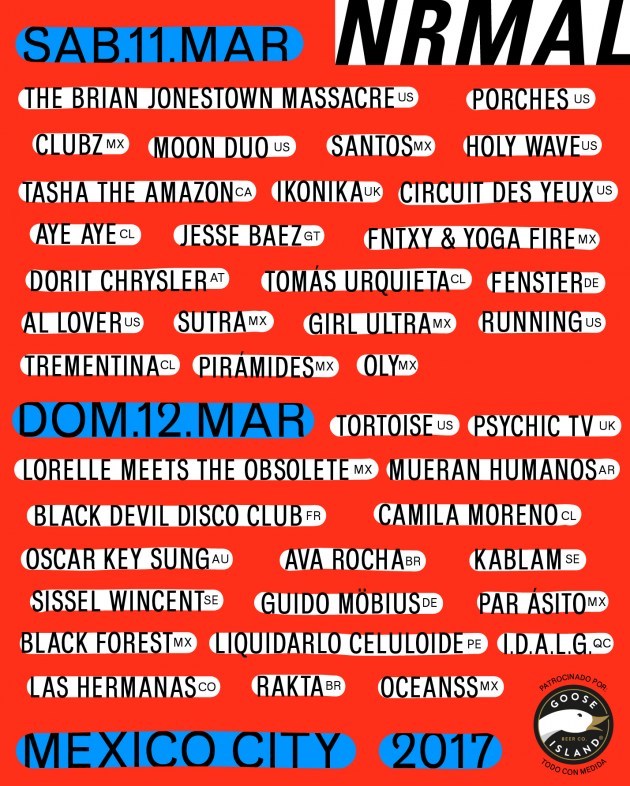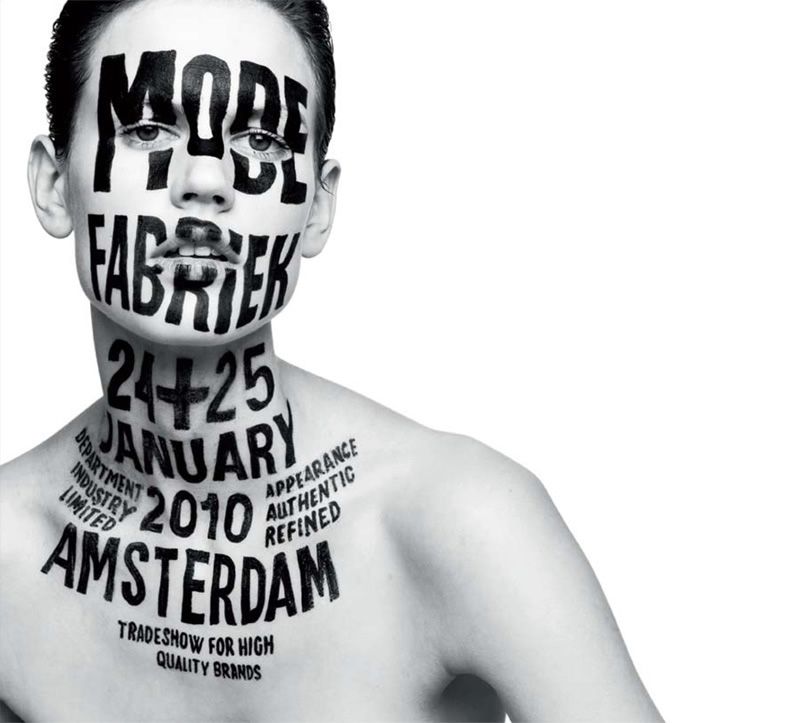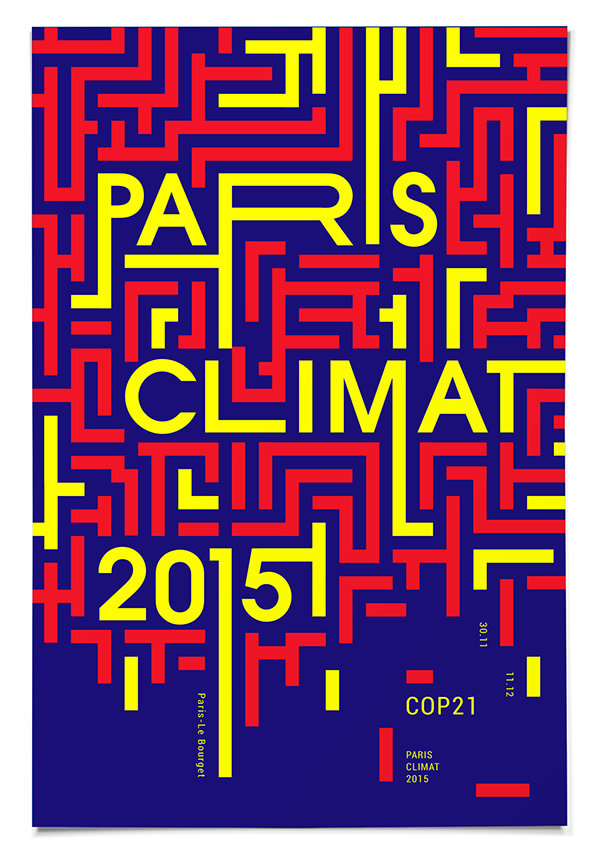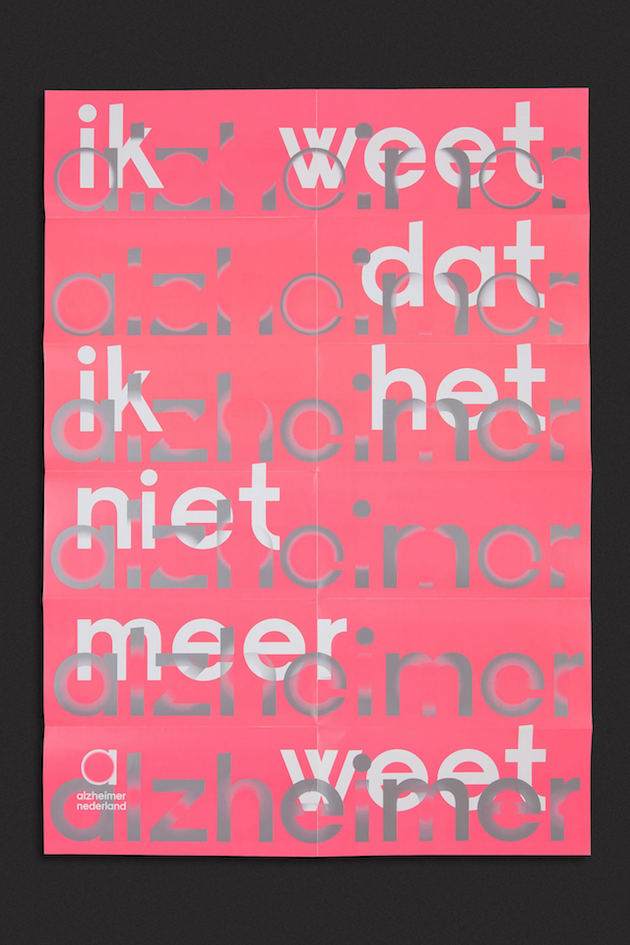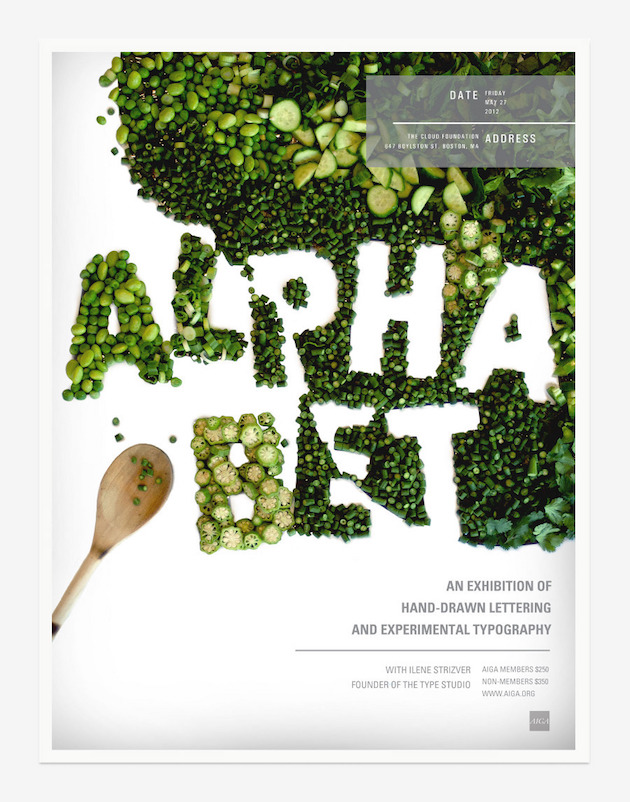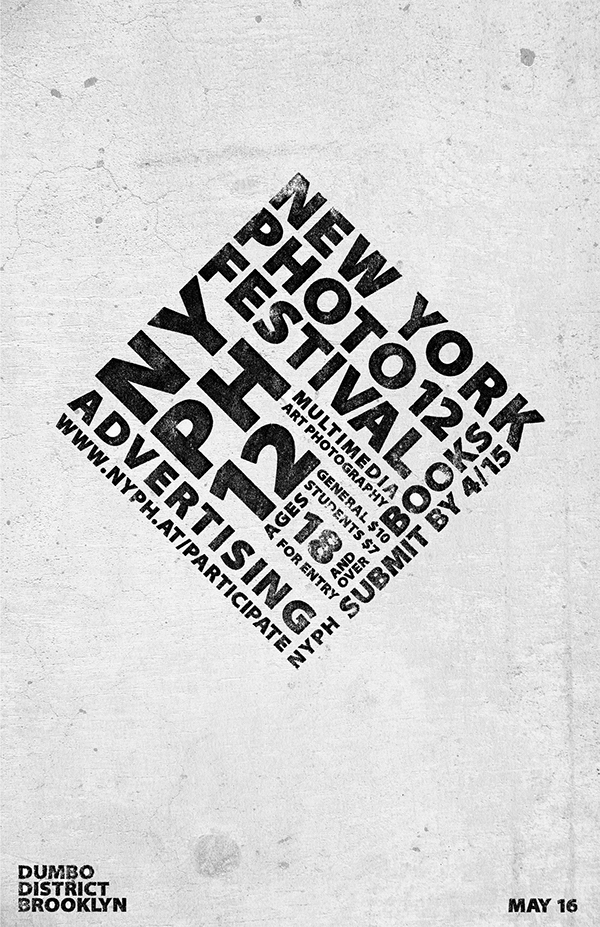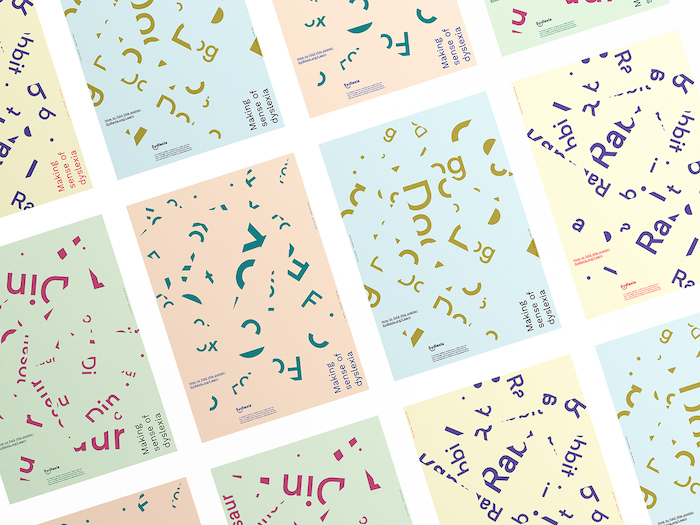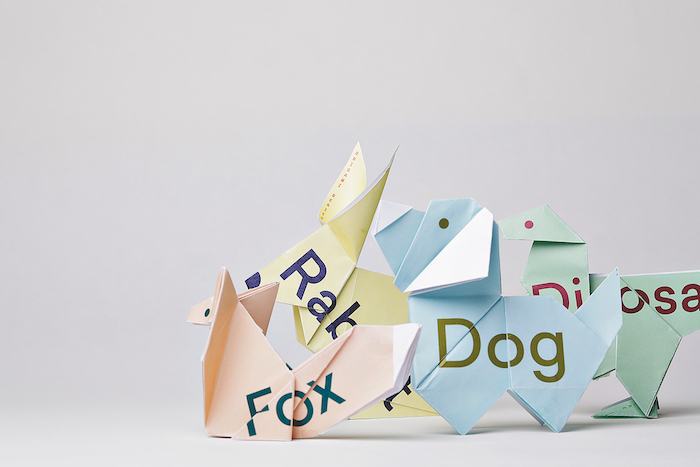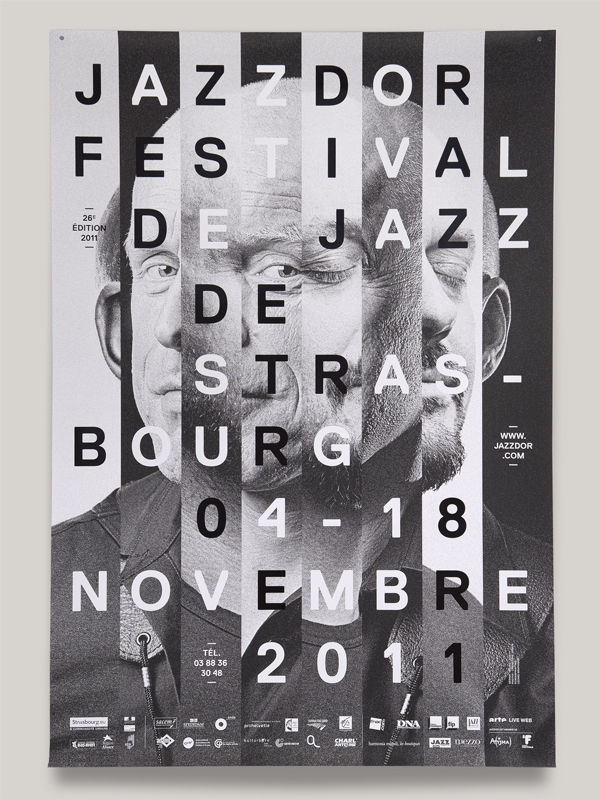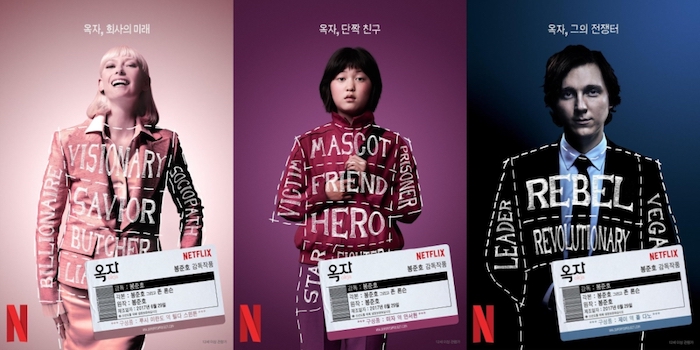
10 affiches publicitaires qui utilisent la typographie avec brio
Une affiche publicitaire, ce n’est pas que des photos ou des illustrations, c’est aussi du texte !
D’où l’importance capitale de la typographie pour créer un poster qui attire l’œil et qui reste gravé dans la mémoire.
Voici justement 10 exemples d’affiches qui utilisent brillamment le texte et les polices d’écriture.
Nrmal est un festival de musique qui a lieu chaque année à Mexico.
Les affiches promotionnelles de l’événement utilisent toujours le texte de manière très prononcée (et efficace), afin de présenter les différents artistes qui y participent, comme en témoigne l’affiche de l’édition 2017.
Créée par Studio Dumbar pour une organisation néerlandaise de lutte contre la maladie d’Alzheimer, cette affiche utilise brillamment la typographie pour communiquer sur ce sujet difficile.
En effet, les caractères flous et partiellement effacés symbolisent la perte de mémoire et l’âge, tout en pouvant être perçus comme une lueur d’espoir.
Toute l’originalité de cette affiche – réalisée par Kittaya Treseangrat – vient des lettres dessinées avec des légumes (ou à l’aide de l’espace vide), lui conférant un aspect vraiment unique.
En parallèle, des polices d’écritures simples et sobres sont utilisées pour le texte d’accompagnement (en haut et en bas à droite) afin de ne pas surcharger le visuel.
Cette affiche utilise habilement le texte pour créer une forme carrée qui ne manque pas d’attirer l’œil et de susciter l’intérêt.
La typographie se veut quant à elle assez sobre, en termes de couleur et de forme ; seul un effet « abîmé » lui a été appliqué, en accord avec le fond grisâtre et fissuré.
À l’instar de l’affiche pour Alzheimer Nederland, ces visuels créés par BBDO Dubaï met en lumière les problèmes de lecture liés à la dyslexie.
Les affiches présentent des mots et des lettres tronqués, et donc incompréhensibles… Mais, une fois pliées comme des origamis, elles dévoilent leur signification :
Imaginée par Helmo pour le festival de jazz Jazzdor, cette affiche combine un visuel puissant, montrant les différentes émotions ressenties par le spectateur, avec une typographie en noir et blanc qui se fond parfaitement dans l’image.
Le film Okja, produit par Netflix, a eu droit à de très belles affiches pour sa promotion.
Ces dernières décrivent les caractéristiques des personnages principaux en les présentant comme différentes pièces de viande, à la manière d’un boucher – ce qui fait écho à la thématique du film. L’effet « dessiné à la craie » est aussi du plus bel effet.
Vous reprendrez bien un petit peu de jazz ?
L’affiche du festival de Guimarães s’avère très créatif dans son utilisation de la typographie, avec ses lettres qui semblent émaner de l’instrument comme des notes de musique.
Mode Fabriek est l’un des principaux événements du monde de la mode aux Pays-Bas.
L’affiche de son édition 2010 s’est avérée particulièrement audacieuse, puisque son créateur a « appliqué » la typographie directement sur le corps d’un mannequin.
Créée dans le contexte de la conférence de Paris de 2015 sur le climat (COP21), cette affiche de Jessica Fecteau utilise habilement les formes et les couleurs pour faire ressortir les mots « Paris », « climat » et « 2015 » au milieu de ce qui ressemble à un labyrinthe.